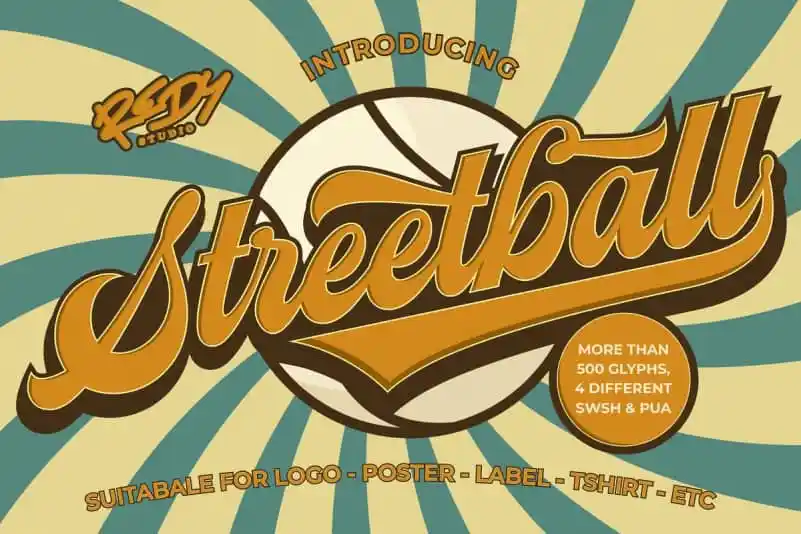
Streetball Vintage Font
Esta é uma fonte script monolínea inspirada em letras manuscritas criada a partir do estilo vintage manual com muitos detalhes. Através desta fonte Streetball, podemos sentir a essência vibrante e sofisticada dos esportes de basebol moderno, misturados com a atmosfera nostálgica e elegante que o tempo trouxe à antiga arte da escrita. Como uma ferramenta prática para designers e artesãos, esta fonte apresenta uma aparência elegante e única, ideal para uso em variadas mídias, desde embalagens até designs de camisetas ou posters, permitindo que você personalize qualquer projeto com um toque único de estilo vintage. Com 511 gílias divididas em vários níveis precisos, esta fonte oferece a flexibilidade necessária para criar uma variedade imensa de resultados, tornando-a perfeita não apenas para aplicação em mídia digital, mas também para trabalhos manuscritos e tipografias.